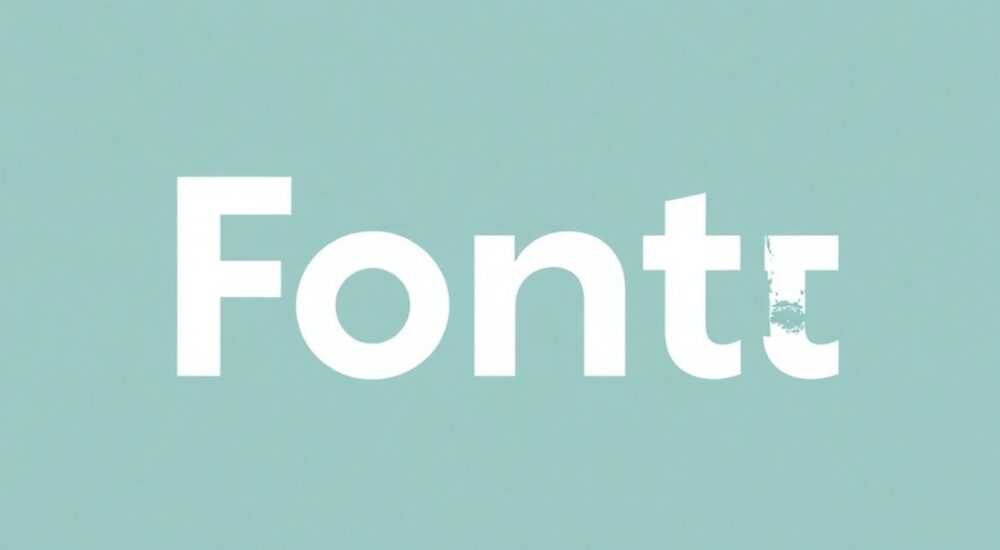
Как использовать шрифт в фотошопе
Работа со шрифтами в Photoshop – это базовый, но крайне важный навык для любого дизайнера или фотографа. Правильно подобранный и настроенный текст способен преобразить любую работу, будь то рекламный баннер, постер или обложка для социальных сетей. Однако начинающие пользователи часто сталкиваются с трудностями при работе со шрифтами: от простого добавления текста до его детальной настройки и стилизации.
Основы работы со шрифтами в Photoshop
Прежде чем погрузиться в тонкости работы, важно понять базовый принцип: Photoshop предоставляет практически неограниченные возможности для работы с текстом, но требует четкого понимания инструментов. Добавление текста начинается с выбора инструмента «Текст» (горячая клавиша T), который позволяет создать как простые текстовые блоки, так и сложные многострочные композиции.
- Инструмент горизонтального текста
- Инструмент вертикального текста
- Текстовый блок с автоматическим переносом
- Точечный текст без ограничений рамкой
Пошаговое руководство по добавлению и настройке шрифтов
Для эффективной работы со шрифтами в Photoshop необходимо следовать определенной последовательности действий:
- Выберите инструмент «Текст» на панели инструментов
- Установите начальную точку кликом мыши или создайте текстовую рамку
- Настройте базовые параметры через верхнюю панель свойств
- Отрегулируйте дополнительные параметры через панель «Символ»
Параметр |
Функция |
Горячие клавиши |
Размер шрифта |
Изменение масштаба текста |
Ctrl+Shift+> / Ctrl+Shift+
|
Межсимвольный интервал |
Регулировка расстояния между буквами |
Alt+стрелки влево/вправо |
Межстрочный интервал |
Настройка расстояния между строками |
Alt+стрелки вверх/вниз |
Расширенные техники работы со шрифтами
Профессиональная работа предполагает использование продвинутых методов форматирования текста. К таким методам относятся:
- Создание текстовых эффектов через стили слоев
- Применение деформации текста (Warp Text)
- Использование масок для создания уникальных текстур
- Контурирование текста по заданной форме
Особое внимание стоит уделить работе с текстовыми стилями. Через панель «Стиль» можно быстро применять комплексные настройки к текстовым слоям, что значительно ускоряет процесс работы над проектом. Например, комбинация градиентной заливки с тенью может создать эффект объемного текста всего за несколько кликов.
Подключение и управление шрифтами
Тип шрифта |
Характеристики |
Рекомендации по использованию |
Serif |
Наличие засечек |
Подходит для печатных изданий |
Sans-serif |
Отсутствие засечек |
Идеален для цифровых медиа |
Script |
Напоминает рукописный текст |
Хорош для заголовков |
Эффективные практики работы с текстом
Вот несколько профессиональных советов, которые помогут улучшить качество работы со шрифтами:
- Используйте правило контраста: сочетайте шрифты разной насыщенности
- Ограничьте количество используемых шрифтов в одном проекте (не более 2-3)
- Соблюдайте иерархию текста через размер и жирность
- Проверяйте читаемость текста на разных устройствах
Экспертное мнение: Михаил Смирнов, дизайнер с 15-летним опытом
«За годы работы я выработал несколько ключевых принципов работы со шрифтами в Photoshop. Во-первых, всегда оставляйте запас места вокруг текста – это поможет избежать проблем при экспорте. Во-вторых, не бойтесь экспериментировать с наложениями и прозрачностью. Особенно эффективна техника, когда текст частично перекрывается графическими элементами.»
По словам эксперта, одна из распространенных ошибок новичков – чрезмерное использование эффектов. «Часто вижу работы, где буквально каждый символ имеет свою тень, свечение и обводку. Это только мешает восприятию. Лучше сосредоточиться на одном-двух акцентах,» – делится Михаил.
Ответы на частые вопросы
- Как установить новый шрифт в Photoshop?
- Скопируйте файл шрифта в папку Fonts операционной системы
- Перезапустите Photoshop для применения изменений
- Альтернативно можно использовать функцию «Install Font» через меню шрифтов
- Почему некоторые шрифты не отображаются корректно?
- Это может быть связано с отсутствием необходимых символов в наборе шрифта
- Проверьте кодировку документа и совместимость шрифта
- Как создать собственный стиль текста?
- Настройте все необходимые параметры текстового слоя
- Сохраните стиль через панель «Стиль слоя»
- Стиль будет доступен для быстрого применения в будущем
Современные тренды в работе со шрифтами